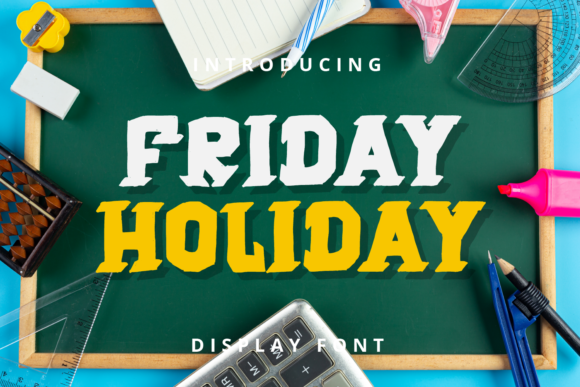
Friday Holiday - это жирный и толстый шрифт, который отлично работает с конструкциями, связанными со спортом, скоростью, гонками или властью. Повеселитесь с этим красивым шрифтом и изучите его бесконечные вариации.